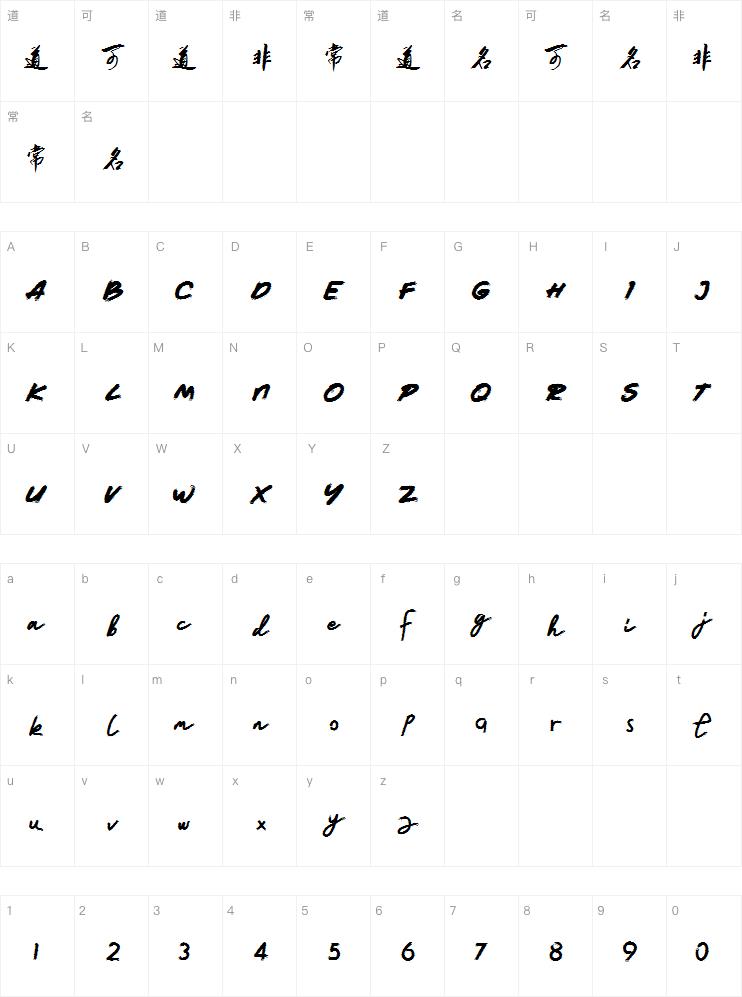
国风悟空行书简体,是一款颇具特色的字体。它将行书的灵动洒脱与国风元素相融合,笔画流畅自然,兼具传统书法的韵味与现代设计的简洁感。在书写风格上,既保留了行书行云流水的书写特质,又通过独特的字形设计,营造出富有 “悟空” 般灵动、不羁的气质,为文字增添了别样的艺术魅力,适用于各类国风主题的设计、文创产品以及书法艺术创作等场景,能很好地传递出传统文化与创新设计结合的美感。